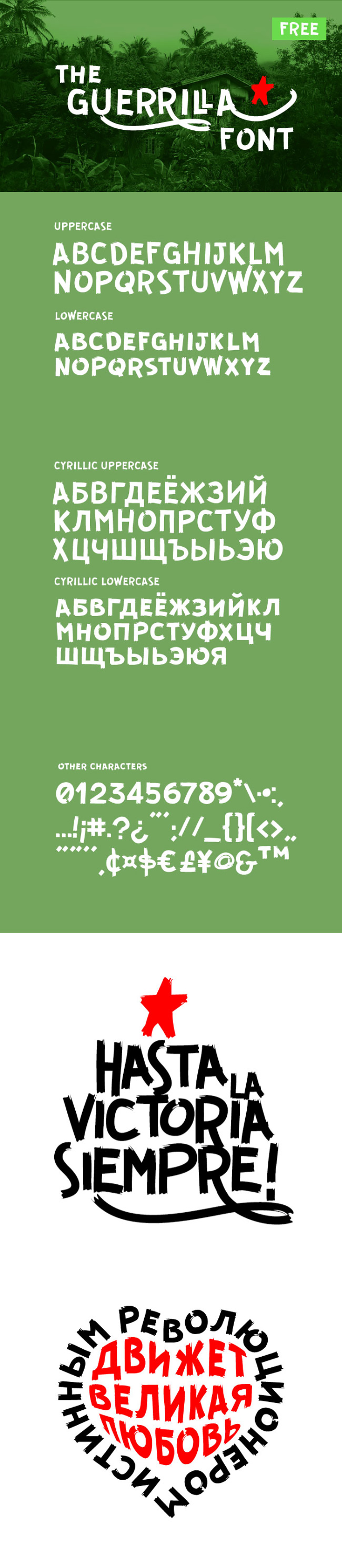
Ну а как тогда сделать такие буквы с хвостиками? У меня такого нет в данном шрифте ...
Sava Savach, Зайдите в меню Окно- Глифы. В нём будут дополнительные символы (некоторые буквы с "хвостами") Выделите в тексте нужную букву и сделайте двойной клик по нужному символу в этой панели.